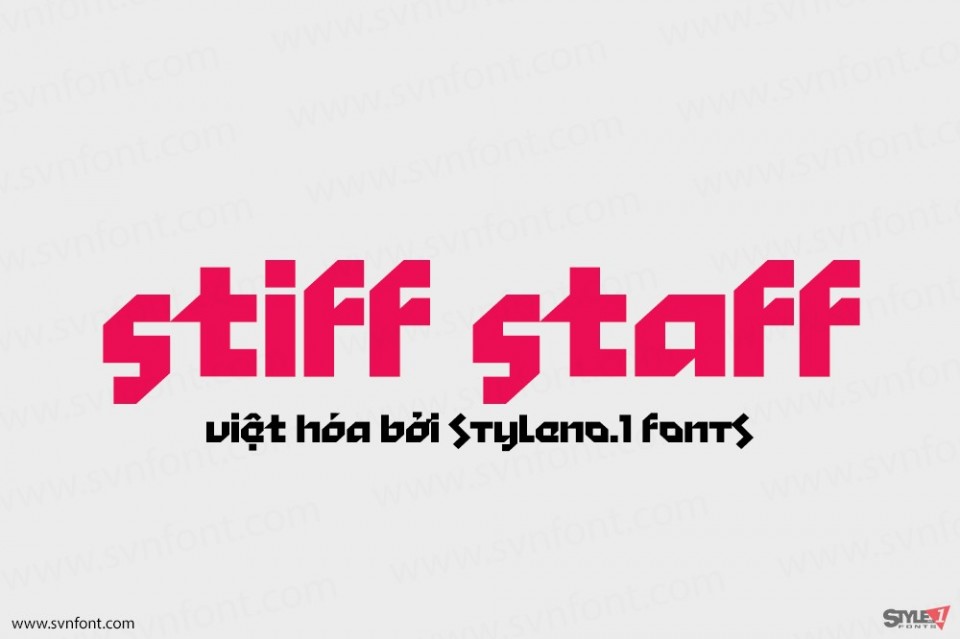
Tải Ngay Font việt hóa SVN Stiff Staff – Bộ Font Độc Đáo Cho Thiết Kế Thổi bùng cảm hứng sáng tạo với Font việt hóa SVN Stiff Staff, một lựa chọn hoàn hảo cho cộng đồng thiết kế đồ họa tại Việt Nam. Khi tìm kiếm một Font Miễn Phí có cá tính mạnh, bạn chắc chắn không nên bỏ qua tác phẩm này. Stiff Staff được thiết kế bởi tác giả Borislav Petrov, mang phong cách trang trí hình học vô cùng đặc biệt. Phiên bản SVN đã được chỉn chu từng nét dấu tiếng Việt, giúp người dùng dễ dàng ứng dụng vào mọi dự án từ học tập đến công việc chuyên môn mà không lo lỗi hiển thị.
Đặc điểm nổi bật của Font việt hóa SVN Stiff Staff
Phong cách thiết kế hình học tinh tế
Font việt hóa SVN Stiff Staff gây ấn tượng bởi những đường nét sắc sảo, góc cạnh nhưng vẫn giữ được sự cân đối tuyệt vời. Đây là dạng font không chân với các cấu trúc hình khối đặc trưng, tạo nên cảm giác hiện đại và đầy tính nghệ thuật cho văn bản.
Tính ứng dụng linh hoạt trong giáo dục và đồ họa
Với sự rõ ràng trong từng ký tự, bộ font này cực kỳ phù hợp để làm tiêu đề báo cáo, bìa sách giáo khoa hoặc các ấn phẩm truyền thông của nhà trường. Sự kết hợp giữa nét cổ điển và hiện đại giúp nó nổi bật trên cả nền tảng in ấn và kỹ thuật số.
Cách sử dụng Font việt hóa SVN Stiff Staff hiệu quả
Ứng dụng trong thiết kế tiêu đề
Hãy sử dụng bộ font này cho các tiêu đề chính (Headlines) để thu hút sự chú ý ngay lập tức. Do đặc thù nét chữ khá dày và cá tính, nó sẽ phát huy tối đa sức mạnh khi đứng độc lập trên các banner hoặc poster sự kiện lớn.
Kết hợp với các font chữ khác
Để tạo ra sự hài hòa, bạn nên kết hợp Stiff Staff với một font Serif nhẹ nhàng cho phần nội dung chi tiết. Sự tương phản này sẽ giúp bố cục thiết kế trở nên chuyên nghiệp và dễ đọc hơn đối với người xem.
Kết luận về bộ font chữ ấn tượng